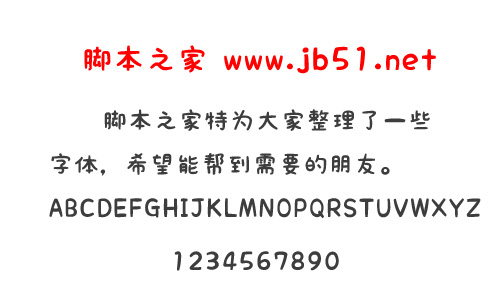
【何尼瑪】土肥圓字體又可以稱之為海報(bào)圓圓字體,是一款以黑體字體為原形變形的字體,字體變形卡通化,非常具有趣味性,可廣泛應(yīng)用于平面設(shè)計(jì)、廣告設(shè)計(jì)、報(bào)紙雜志、正文標(biāo)題等領(lǐng)域,歡迎有需要的朋友前來(lái)下載使用。